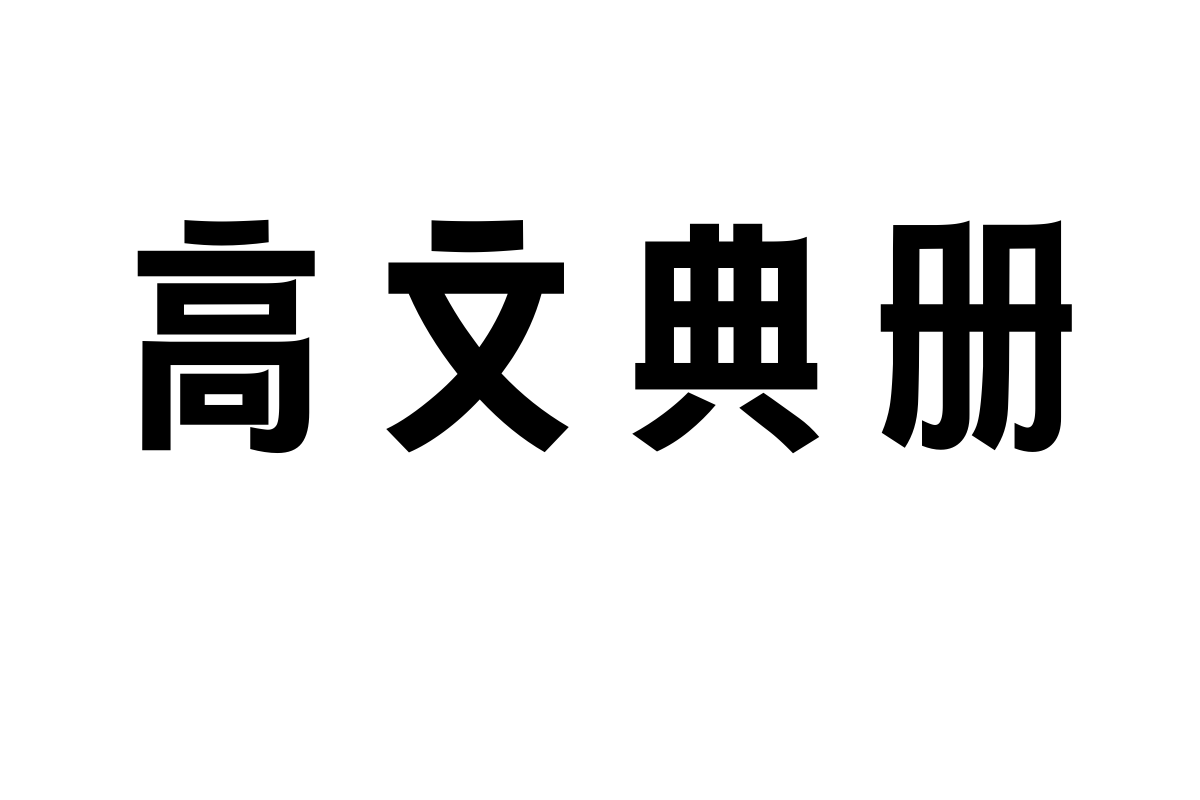
文道古典黑字体是一款具有独特韵味和艺术感的中文字体。它源自于中国古代书法艺术,经过精心设计和制作而成。这款字体线条流畅,结构严谨,给人一种古朴典雅的感觉。它的笔画粗细适中,既有力度又有柔美,既适合书写正式的文件,也适合用于设计中的标题或文字。此外,文道古典黑字体还具有一定的可读性,能够清晰地传达信息。总之,这款字体是一款值得推荐的优秀中文字体。